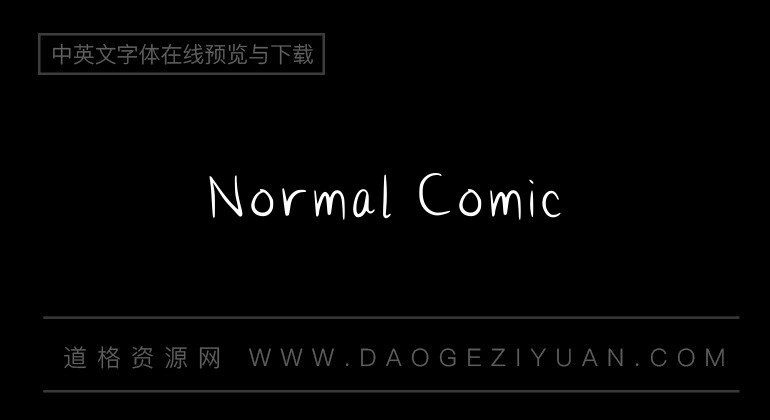
Normal Comic
Normal Comic 是一款漫画风格的字体,它具有明显的漫画风格,笔画粗细有节奏感,字体设计清晰简洁,非常适合用于漫画、动漫、游戏、卡通等领域。它的特点是字符设计简洁,笔画粗细有节奏感,使得字体看起来更加有趣,且具有一定的艺术感。它的笔画设计细腻,使其在小字体大小时也能保持清晰可见。
Normal Comic是一款非常不错的手写艺术字体,具有很好的视觉感,适合于文化类的宣传设计、商业类品牌的广告和产品包装设计以及个性化文字排版等较多场景。